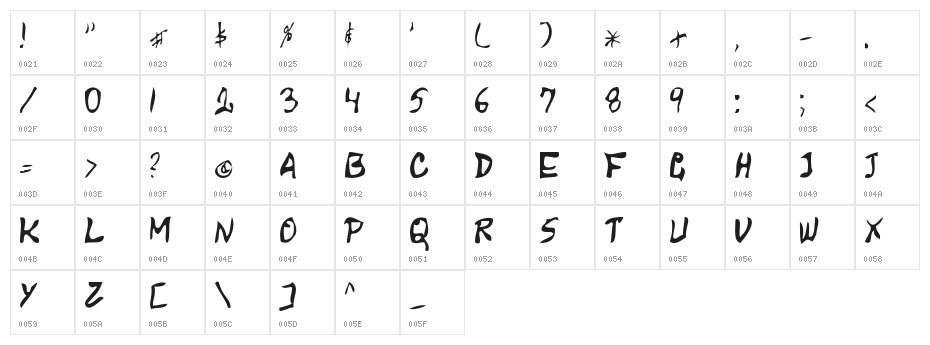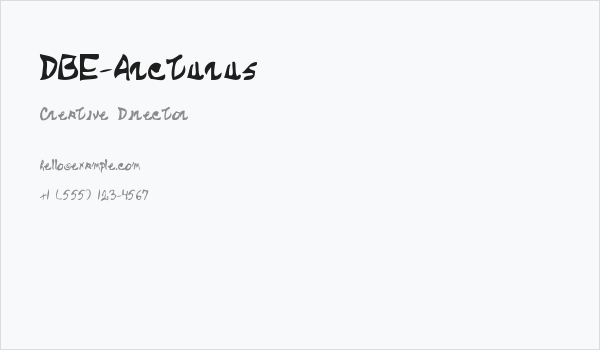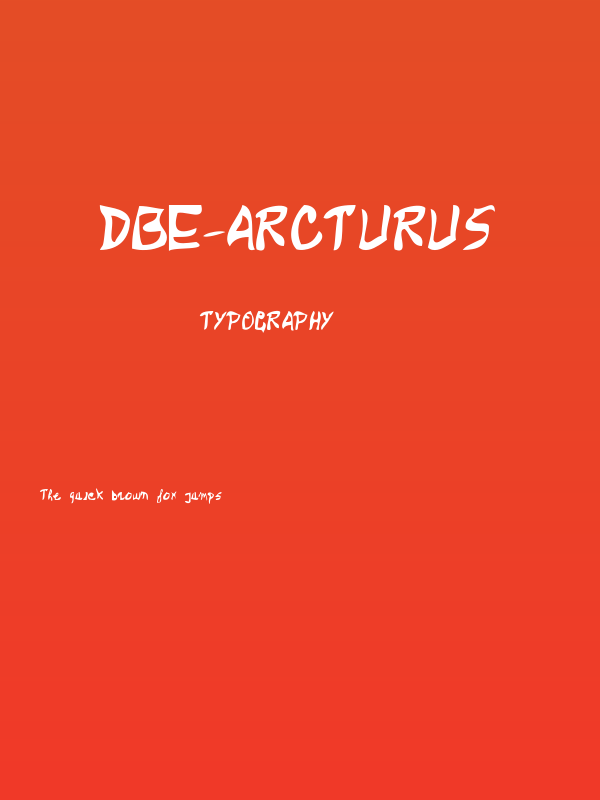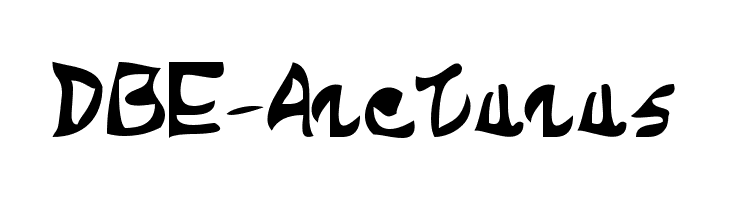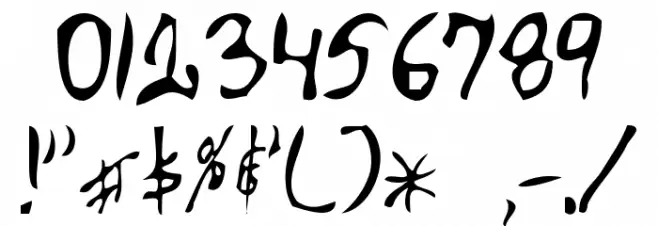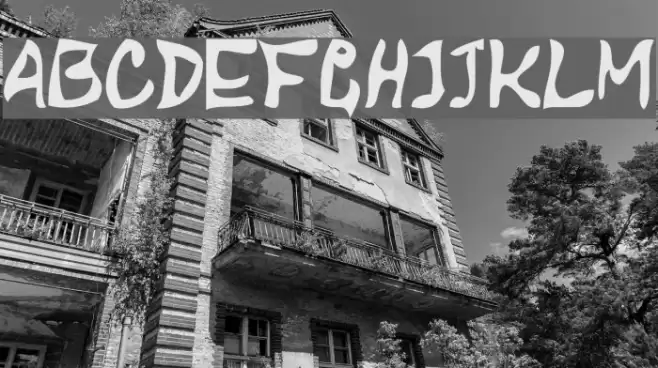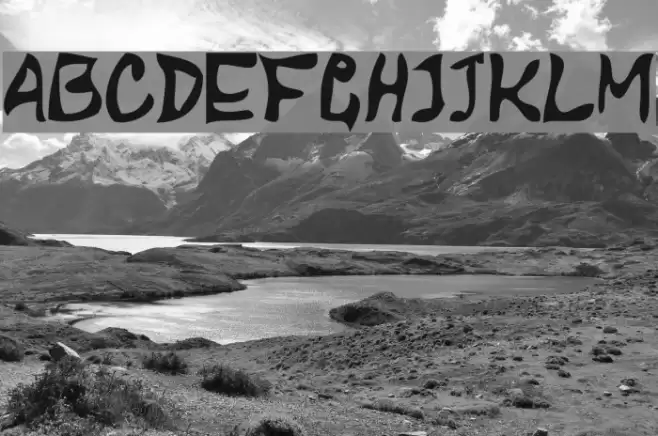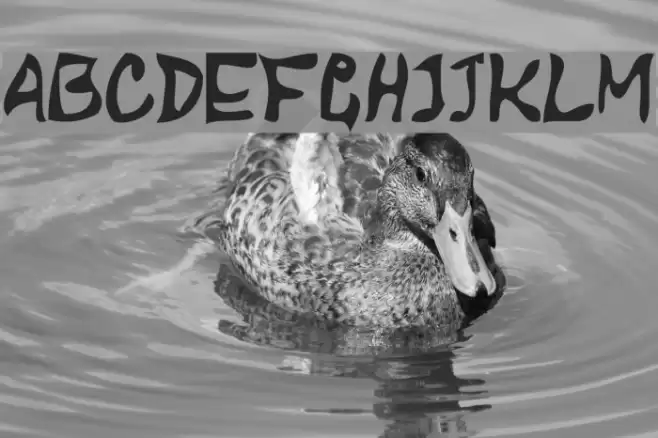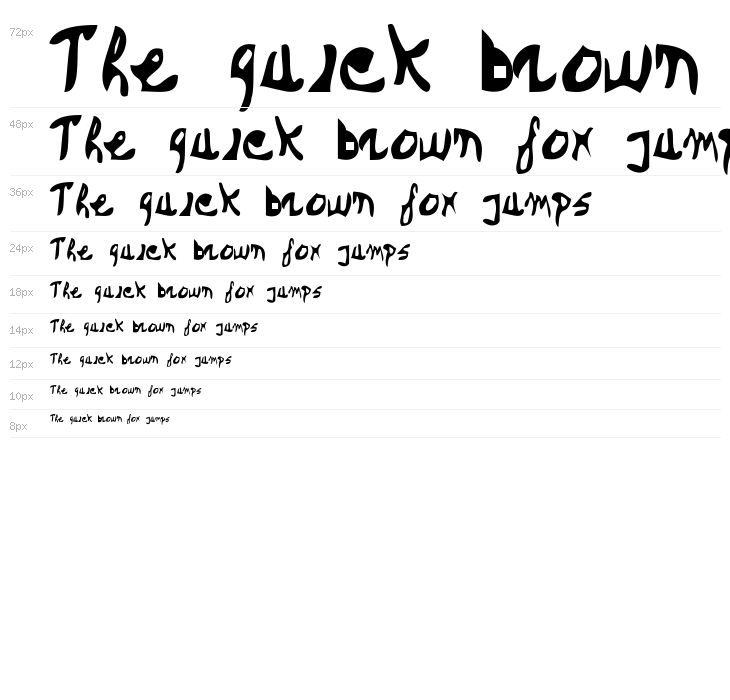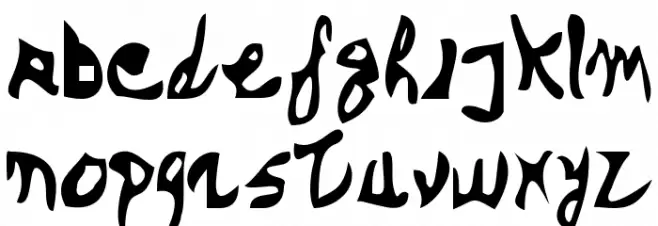
DBE-Arcturus Font
| Style général | Modern, Artistic |
| Projets proposés | Ideal for creative projects such as posters, album covers, street art designs, and branding that requires a bold, artistic touch. |